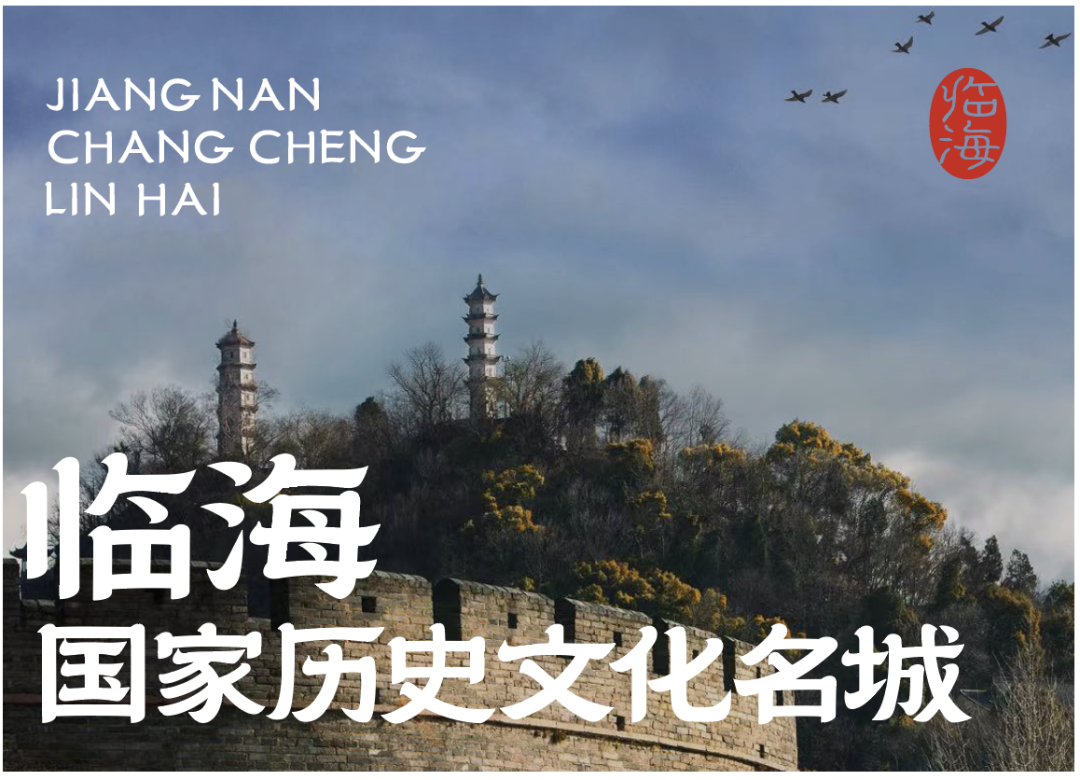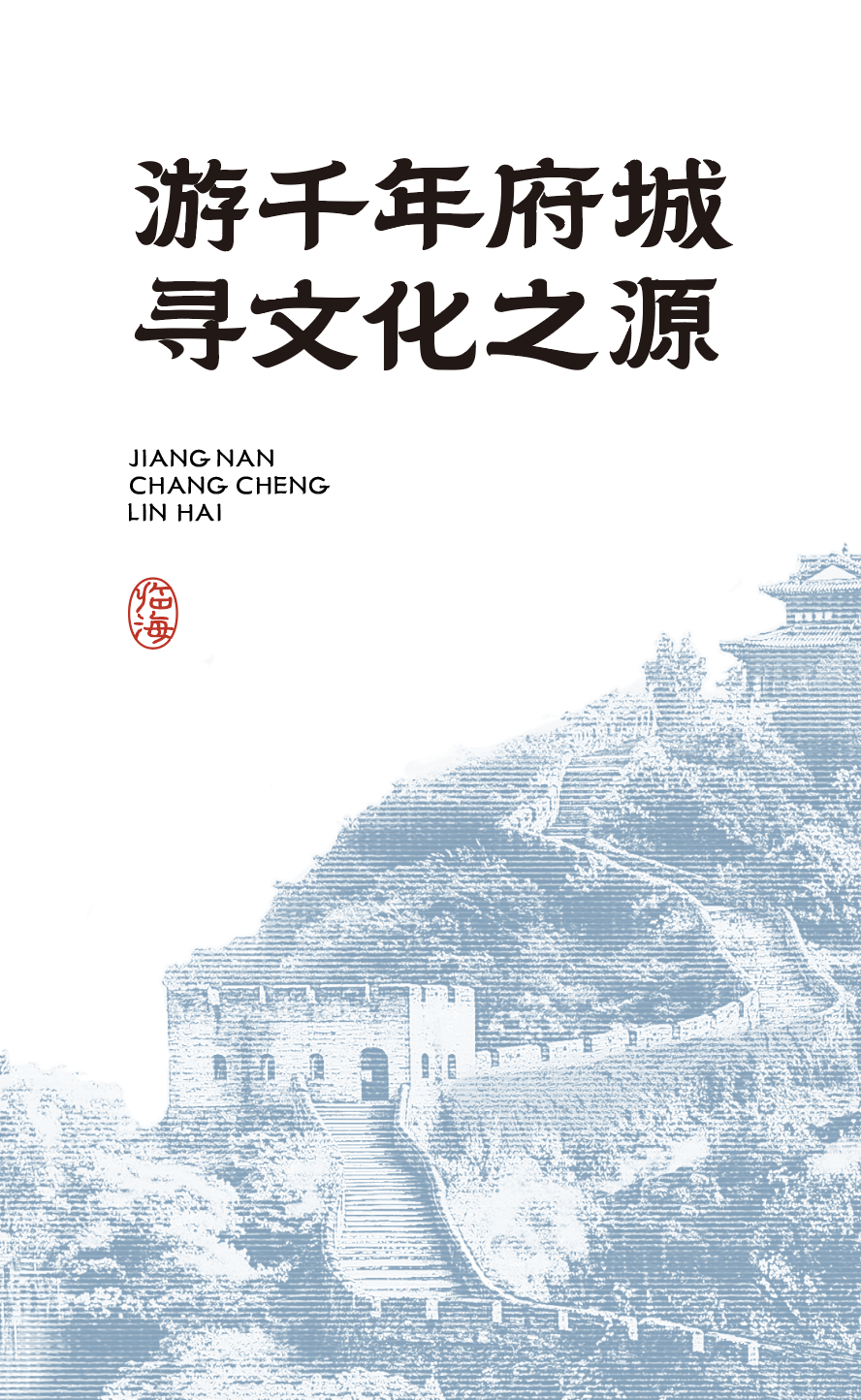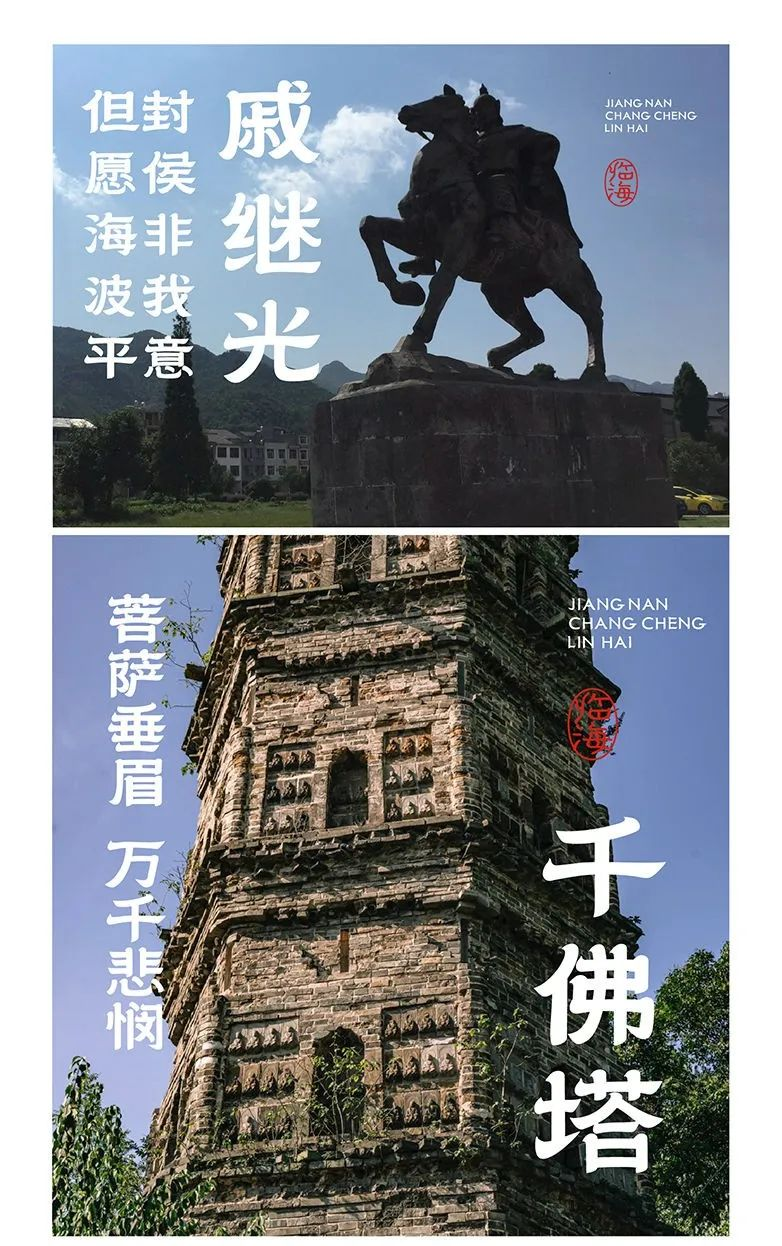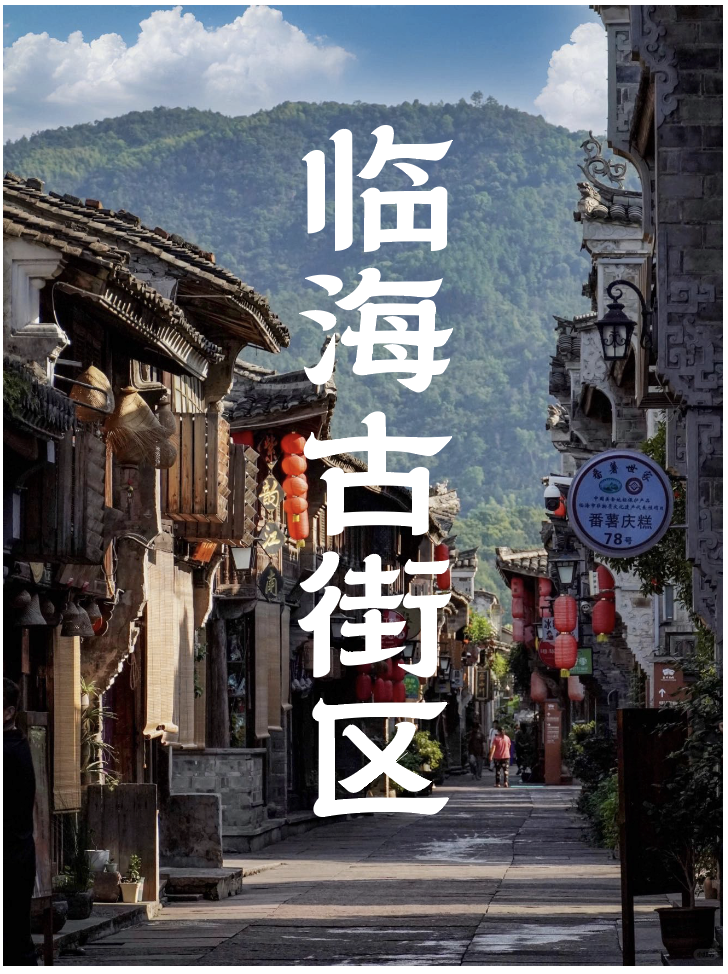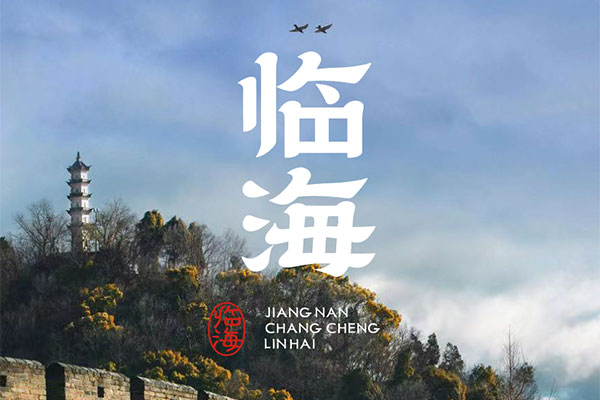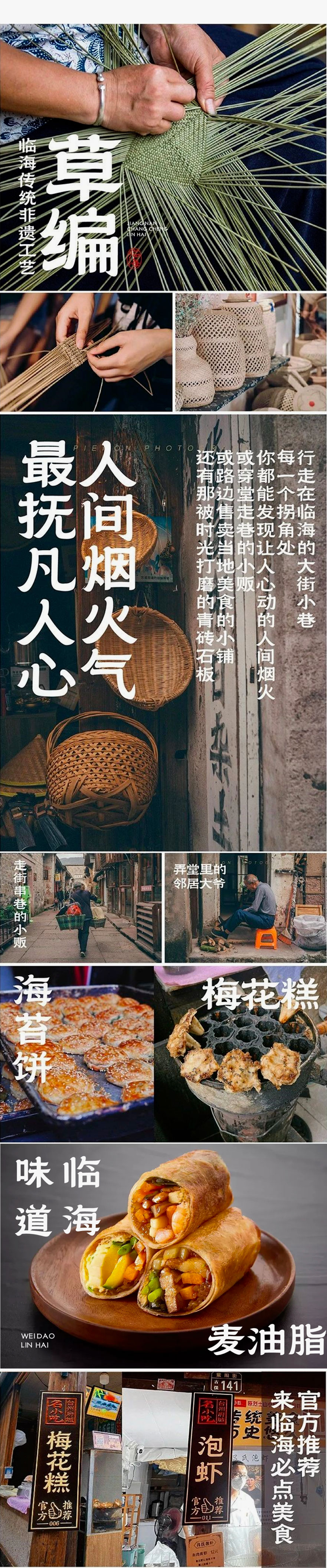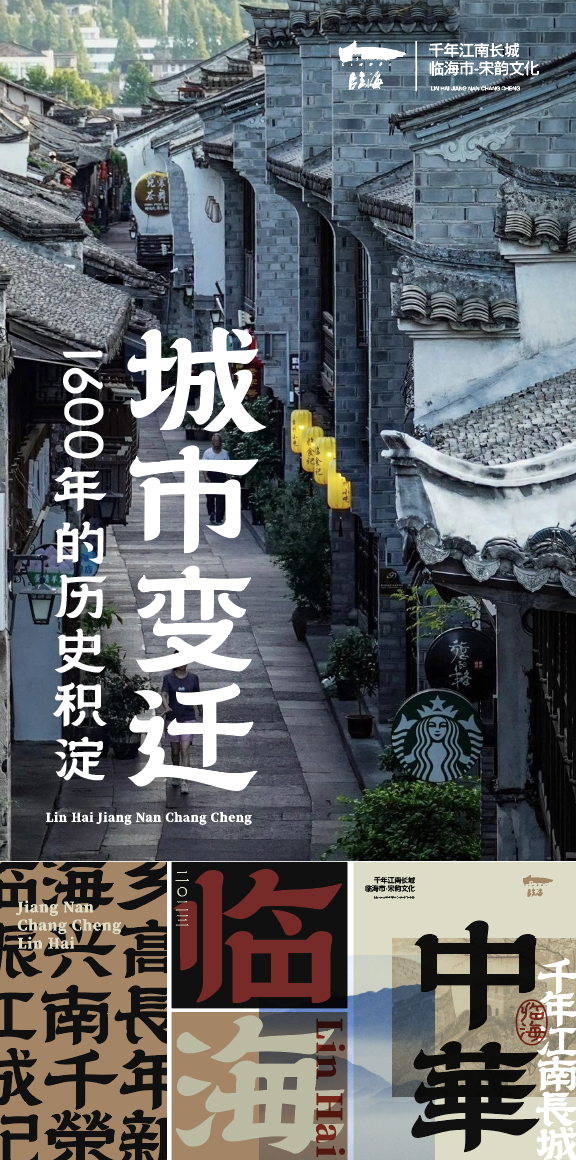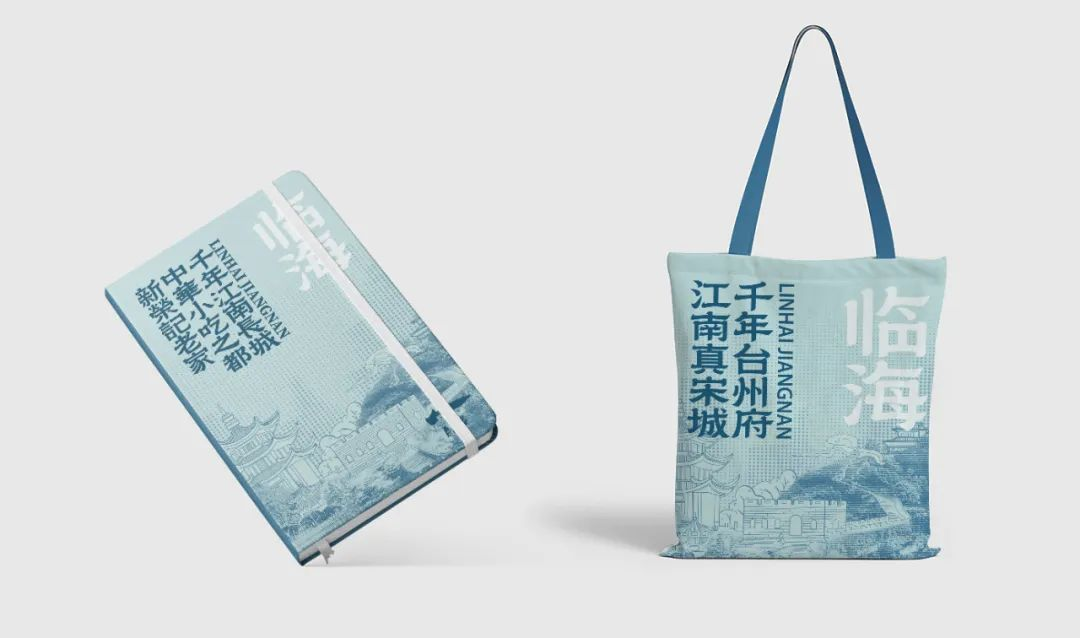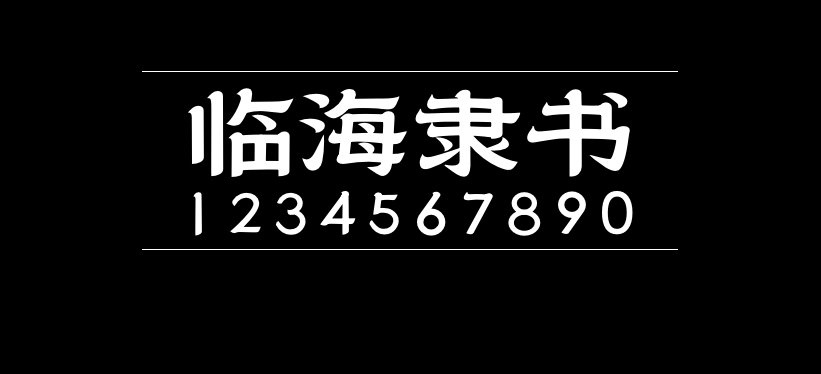
临海隶书
临海隶书是由临海市社发集团与乡立方团队携手打造,推出的一款拥有临海独特风格和时代烙印的专属字体。
一座城市的影响力
取决于城市文化的影响力
经营城市品牌
经营的是一座城市的文化辨识度
……
为持续打响“千年台州府 江南真宋城”
文旅品牌形象
让文化传播更具辨识度
市社发集团积极谋划
深度挖掘临海文化内涵
与乡立方团队携手打造
推出了拥有临海独特风格和时代烙印的
专属字体
临海隶书
台州府城墙、龙兴寺、千年紫阳街等
文化古迹星罗棋布
骆宾王、戚继光、朱自清等
叙说着临海文化绵长的故事
文人舞墨,匠者筑基
共同铸就了临海的文化底蕴
正因如此
临海能较早跻身于“国家历史文化名城”之列
能有信心对世界说“千年古城,最忆临海”
临海隶书
历史底蕴深厚、文化资源丰富
这是临海不可复制的独特禀赋
但如何让世界认识临海呢
源浚者流长,根深者叶茂
文字是文化传承的标志
临海字体
更是传播临海文化的基础元素
一城化一字
一字如一城
站在时光的纵轴上向前望去
隶书的演变史
也是临海城市变迁的缩影
临海隶书
将千年古城、人文繁盛、山水之韵
等临海城市特质
结合汉字五大字体之一的隶书体
隶书,兴盛于汉代
也是临海城市起源的时代
隶书所具有的厚重、古典、拙朴特质
旷达雄浑,古朴内敛
将临海的城市特质展示的淋漓尽致
临海隶书
临海古城,也就是台州府城,始建于晋,扩建于唐,距今已有1600多年的历史。古城原有七门十三敌台,现仅存四门和四座敌台。
江南长城,是江南地区唯一的长城,城墙依山就势,俯视大江,敌楼林立,气势恢宏,是北方明长城的师范和蓝本,人称“江南八达岭”,现存近5000米,目前已列入世界文化遗产预备名单之中。
紫阳古街,全长1080米,是整个古城的中轴线,有“临海第一古街之称”,街道两边的房屋店铺雕梁画栋、古色古香,保留着宋代遗风、明清格局。
在这里,戚继光驰骋海疆“封侯非我意,但愿海波平”。在这里,骆宾王仗剑而起“宝剑思存楚,金锤许报韩”。“莫言沧海阔,杯度自应知”,最澄大师万里求法,化成千佛塔的“菩萨垂眉,万千悲悯”。
临海隶书
无论是临海词调、黄沙狮子、大石车灯、大田板龙、小芝鼓亭、上盘花鼓、城关细吹亭等传统民间文化艺术,还是糟羹、麦油脂、马蹄酥、羊脚蹄、麦饼、蛋清羊尾等传统风味小吃,亦或是刺绣、草编、竹木雕刻等传统工艺。
府城人民的智慧,凝结于千家万户的烟火之中,汇集成千年临海的独特画卷。
临海隶书
通过临海字体打造临海符号化IP
将临海字体融入到城市的
历史、文化、形象、资源、产品、内容
等各个层面
让临海字体成为这座城市
具有独特辨识度和人格化的城市品牌
临海隶书
市社发集团×乡立方
为临海设计的这款临海隶书字体
也可以在招牌、包装上使用它
或许还会在电视、手机上随处看见它
它将带着临海的文化和故事
传播得更远、更广